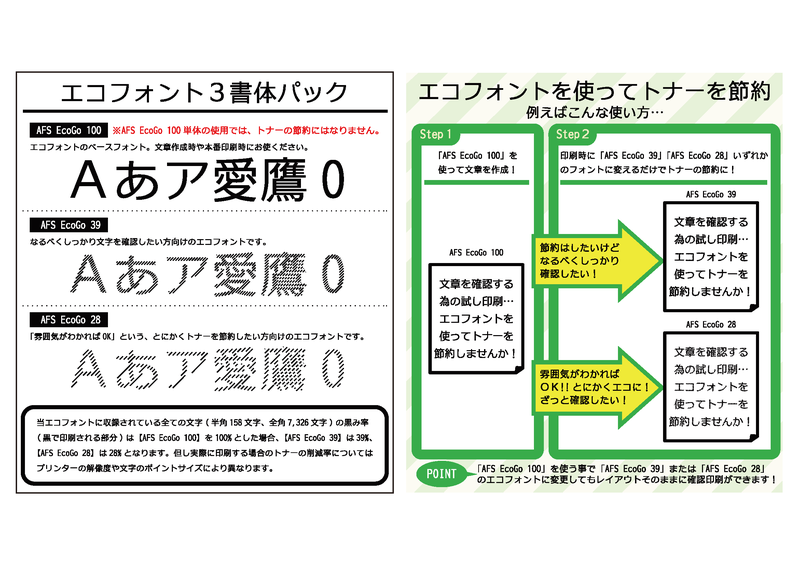
「AFSエコフォント3書体パック」はメイリオデザイナー鈴木竹治氏によるドゥRをベースにしたインクやトナー節約に期待が持てるエコフォントの3書体セットです。
※プレビューフォントはAFSEcoGo28です。
【エコ機能について】
当エコフォントに収録されている全ての文字(半角158文字、全角7,326文字)の黒み率(黒で印刷される部分)は、「AFSEcoGO100」を100%とした場合、「AFSEcoGo39」は39%、「AFSEcoGo28」は28%です。但し、実際に印刷する場合のトナーやインクの削減率については、プリンタの解像度や文字のポイントサイズにより異なります。
「AFSEcoGo100」にはトナーやインクの削減はできません。